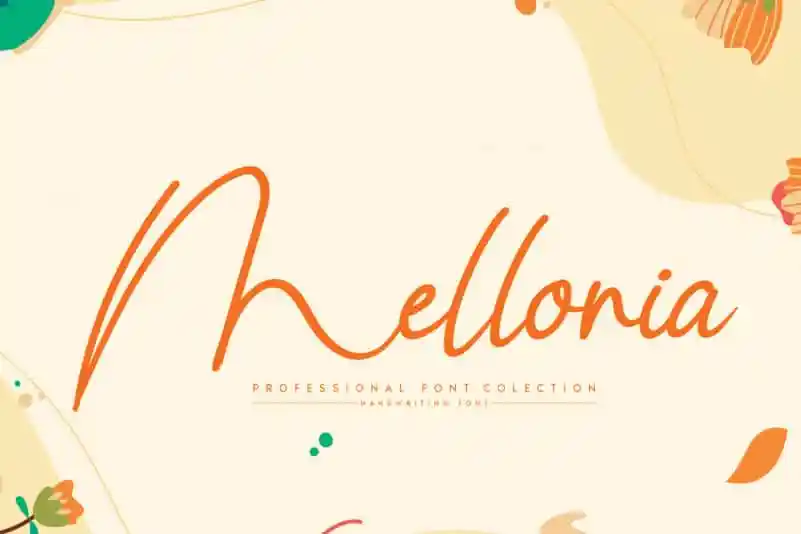
Mellonia Handwritten Font – Download Grátis
Descubra a elegância do Mellonia Handwritten Font, uma fonte feita para aqueles que buscam sofisticação na escrita manual. Describa-a por sua característica fluida e pela delicadeza poética que transborda em cada letra. Seus traços finos e suas formas femininas criam um estilo único e perfeito para qualquer projeto, tornando-o uma escolha excelente tanto para designers profissionais quanto para iniciantes. Suas linhas distintas e seu estilo eterno garantem uma estética que trará a sofisticação de uma carta escrita à mão, ao mesmo tempo em que permite uma versatilidade inigualável. Engane-se apenas um pouco e permita-se ser seduzido pela sua beleza singular, e então utilize-a para criar designs impressionantes. O Mellonia Handwritten Font é mais do que uma fonte: ele é o pincel com o qual você pode pintar seu próximo trabalho de arte digital.